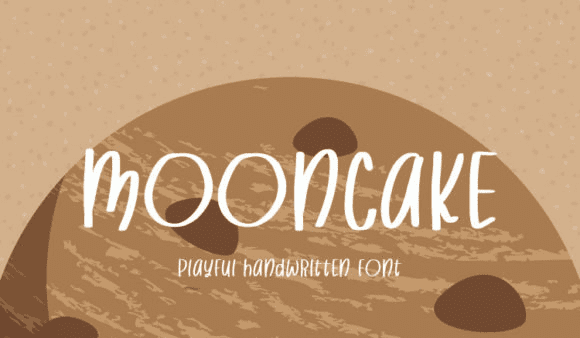
Название: Mooncake Font (2021)
Mooncake - это причудливый шрифт с непринужденной тематикой, отличающийся прекрасным стилем.
Независимо от темы, этот шрифт станет отличным дополнением к вашей библиотеке шрифтов, так как он способен приподнять любое творение.
Название: Mooncake Font (2021)
Mooncake - это причудливый шрифт с непринужденной тематикой, отличающийся прекрасным стилем.
Независимо от темы, этот шрифт станет отличным дополнением к вашей библиотеке шрифтов, так как он способен приподнять любое творение.